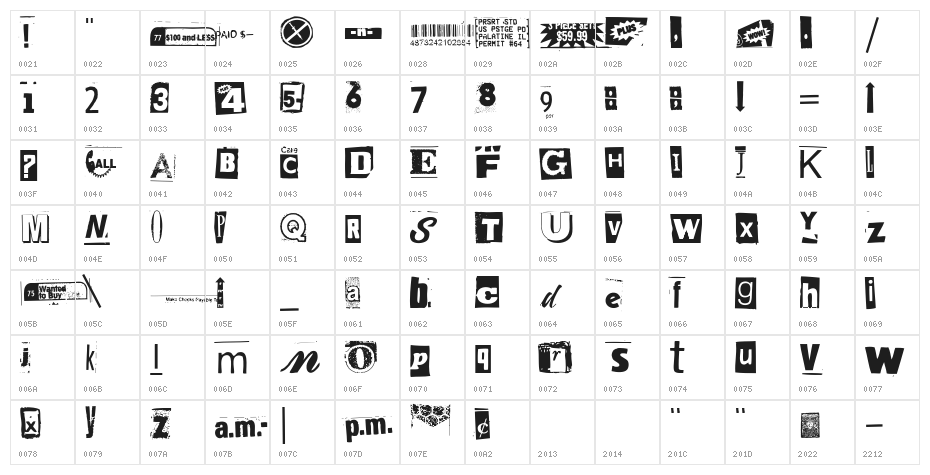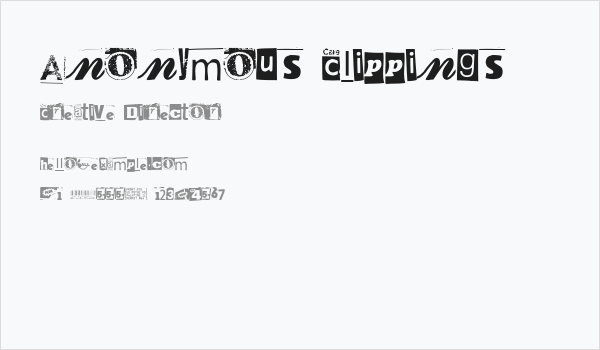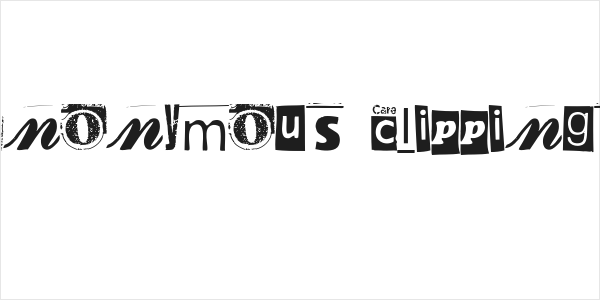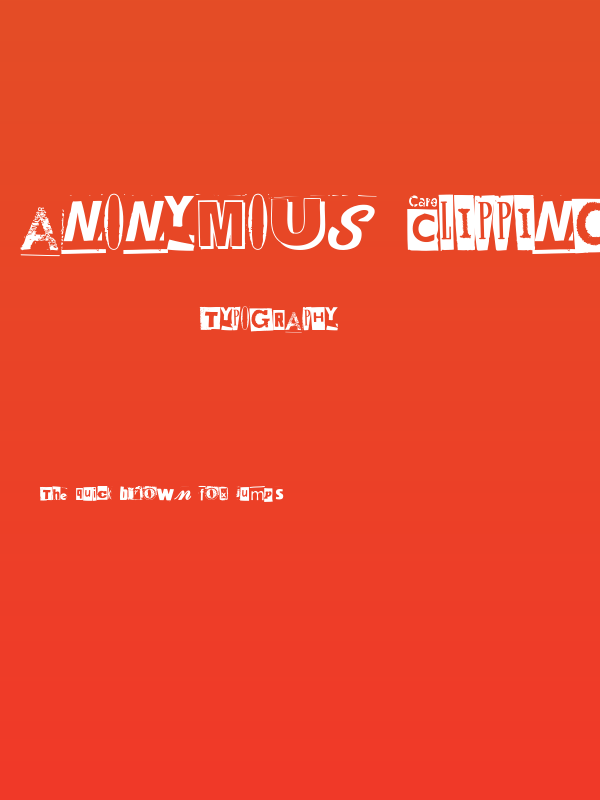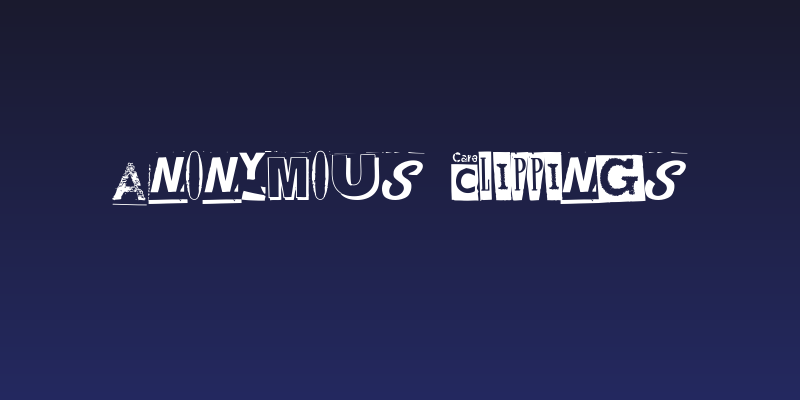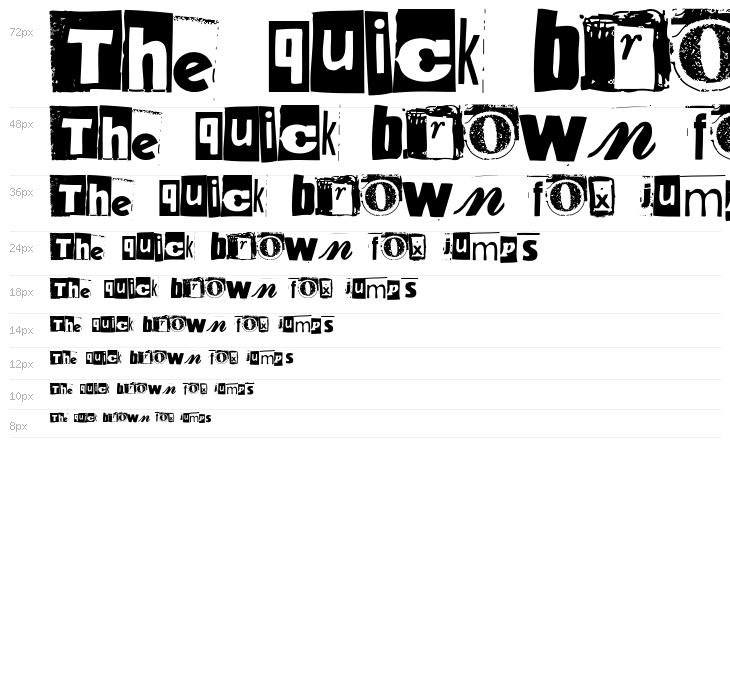
Anonymous Clippings Font
✎ Crazy
| 分类 | Crazy |
| 整体风格 | Vintage, Grungy, Eclectic |
| 使用场景 | Logos, Posters, Album Covers |
| 推荐项目 | Ideal for use in mystery-themed posters, edgy graphic designs, album covers, or any project needing a unique, eclectic look. |